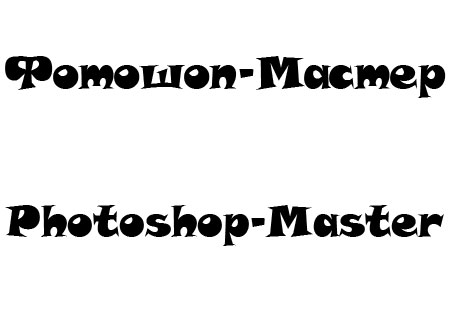
Пасибки за шрифт! Пригодился! Забавный и симпотичный!
Шрифт очень хороший и хорошо работает на обоих языках
Прекрасный шрифт !
Какой хорошенький!!!
"Толстяк" просто супер!!!
Очень интересный шрифт! Попробую. Спасибо!
Бабл! То что надо, спасибо
действительно, очень симпатичный и забавненький ))
Пасиб оч хороший шрифт
Очень даже ничего!